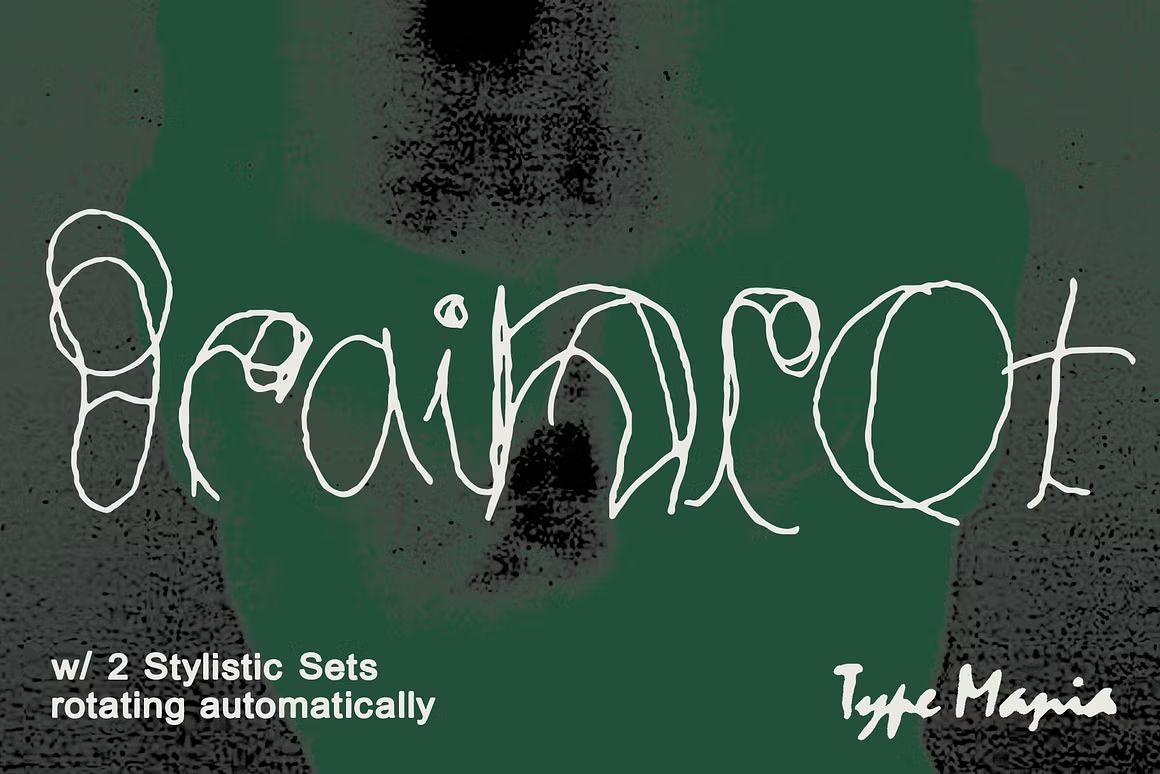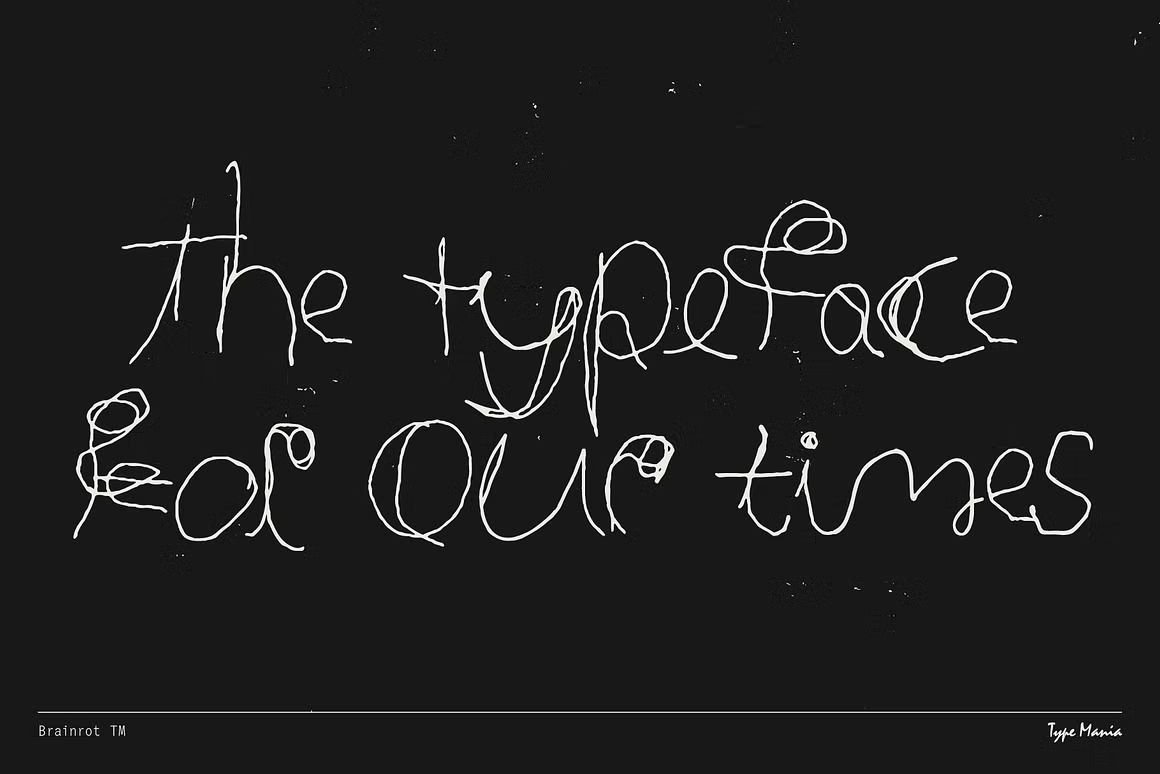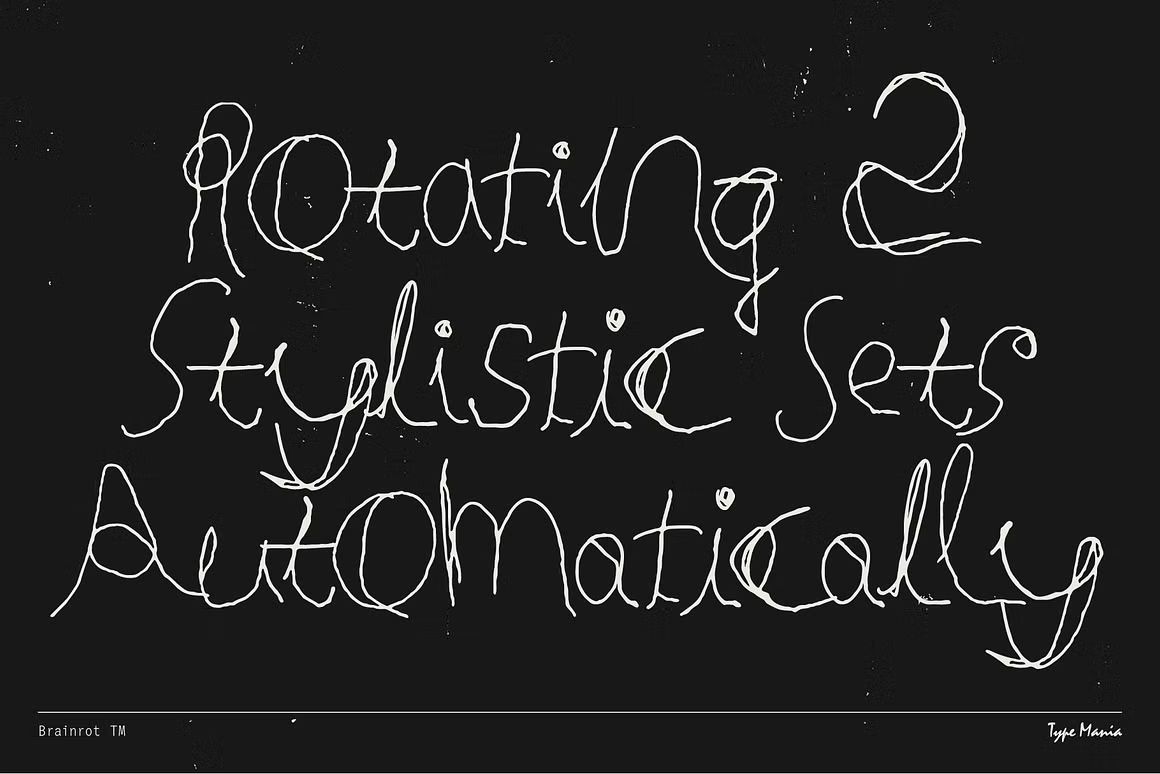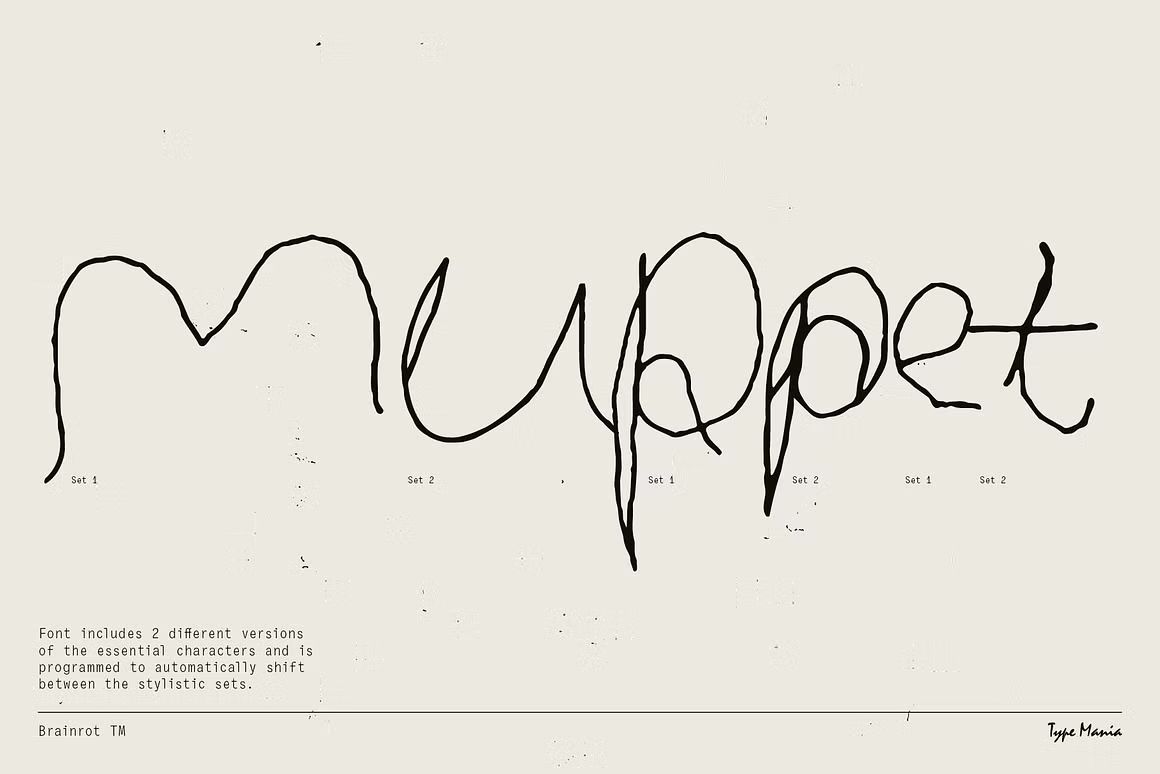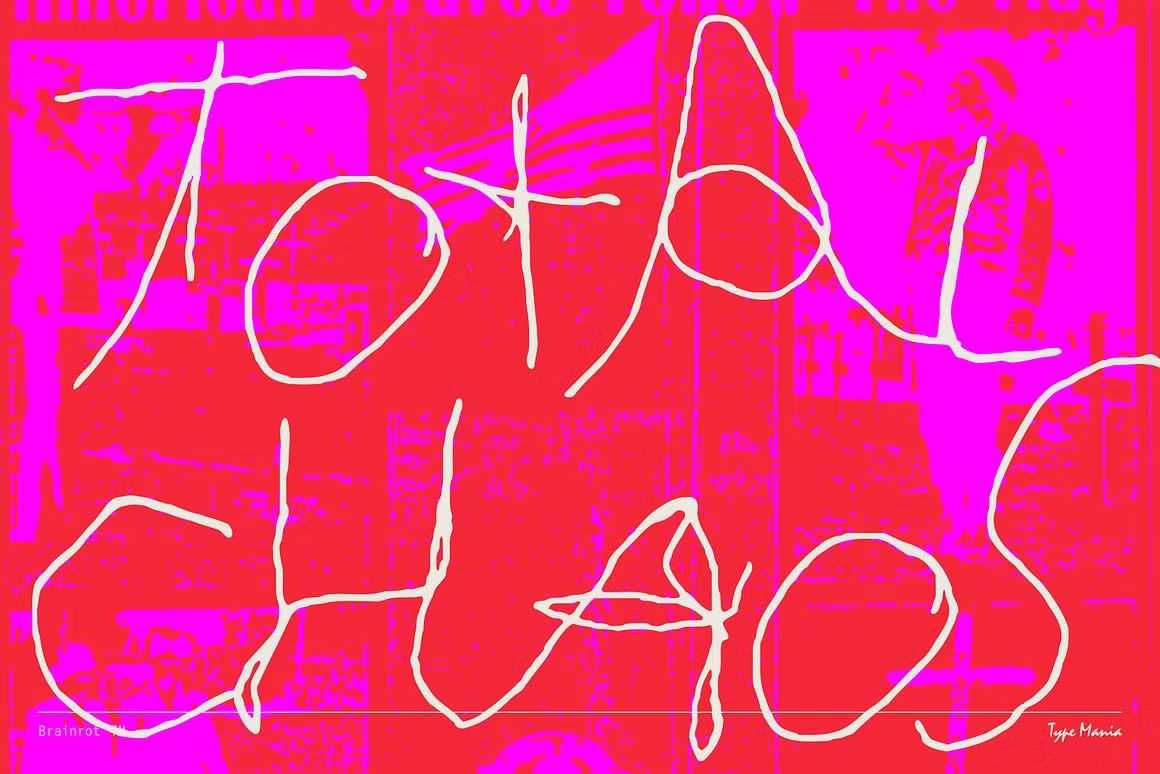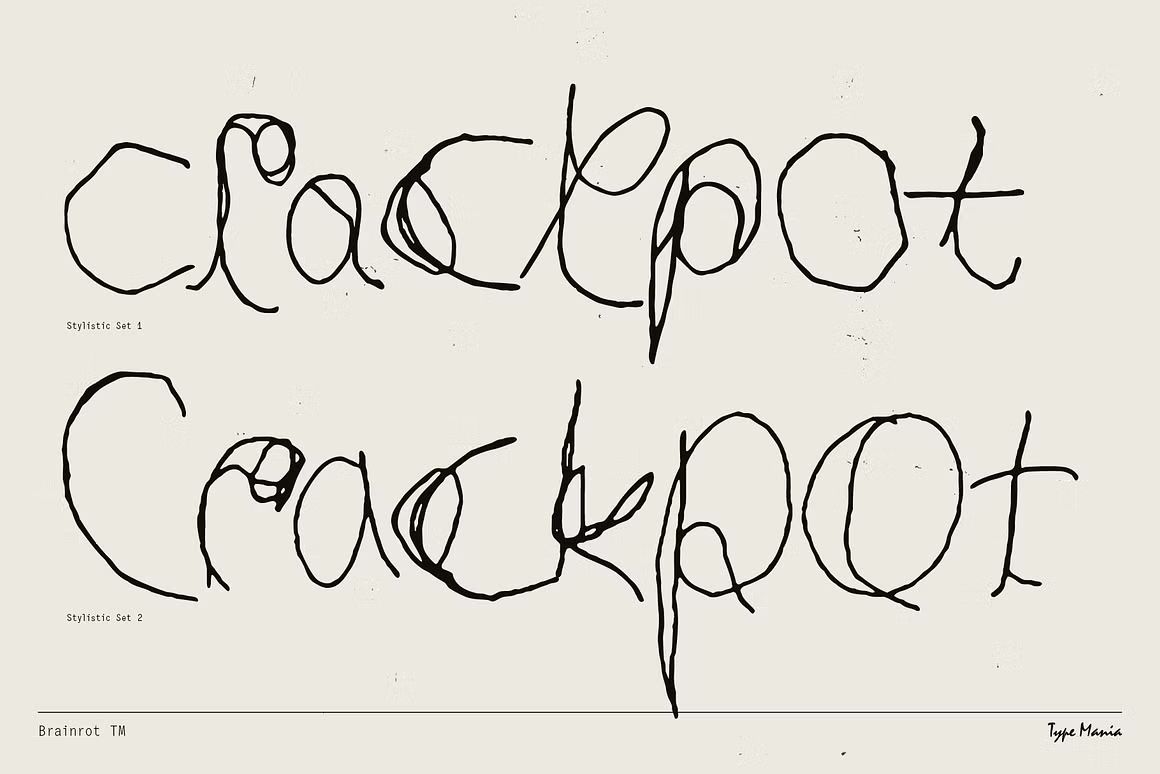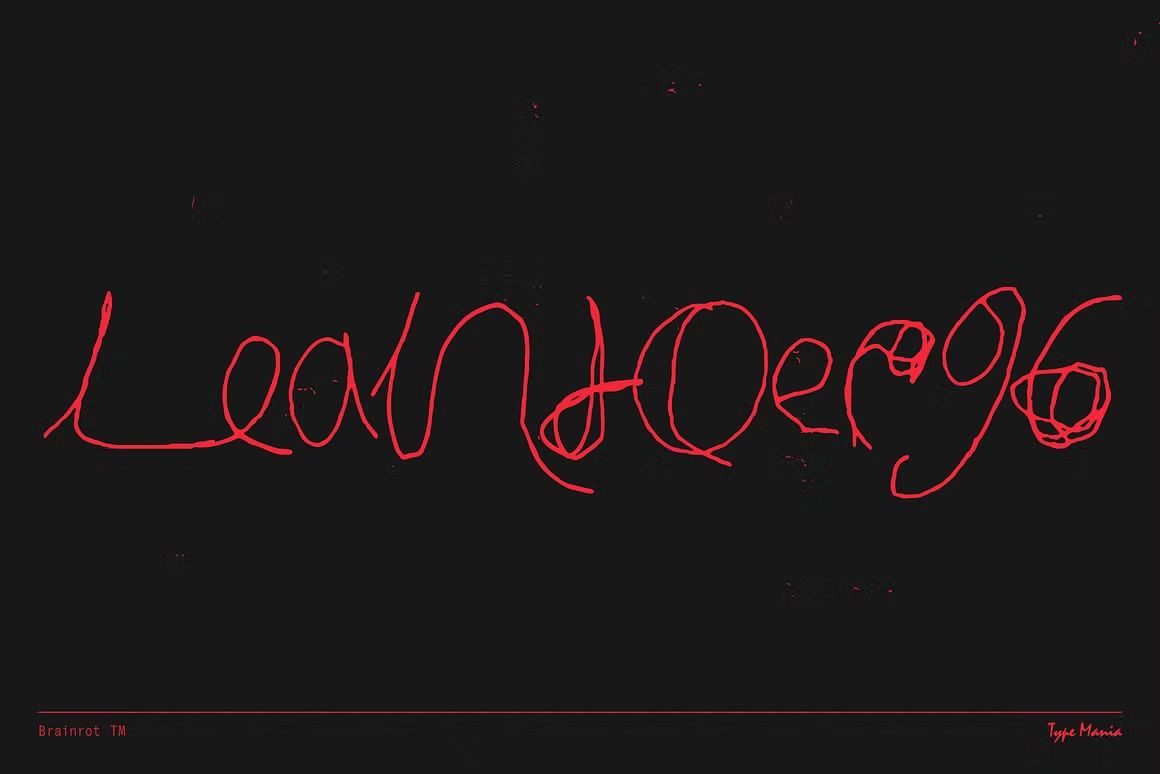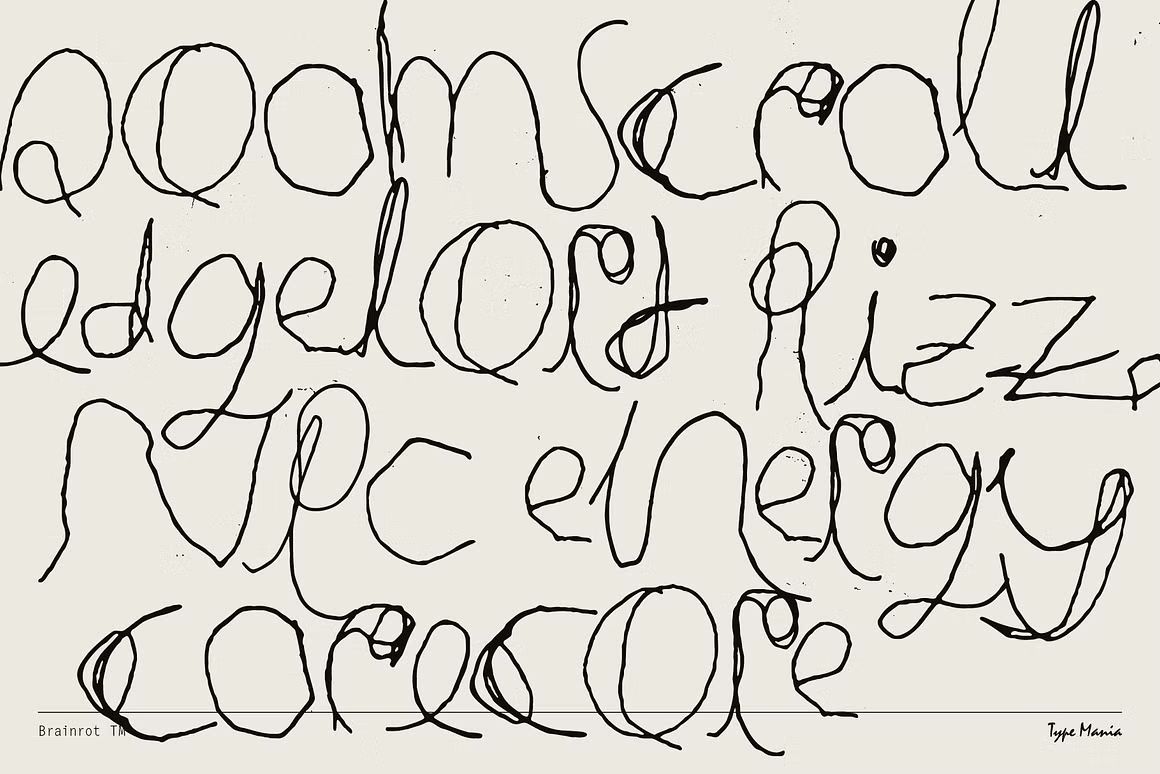
Brainrot TM – Handwritten Font
Brainrot TM adalah font handwritten ekspresif dan liar, cocok untuk desain alternatif dan kreatif. Format OTF/TTF/WOFF, siap digunakan.
Brainrot TM adalah font handwritten bergaya ekspresif dan penuh energi, dengan goresan kasar dan bentuk huruf tak beraturan yang menciptakan kesan bebas, kreatif, dan sedikit “liar”. Sangat cocok untuk desain alternatif seperti poster musik, cover album, zine, ilustrasi indie, atau branding yang ingin tampil unik dan anti-mainstream. Brainrot TM adalah pilihan tepat untuk karya penuh kepribadian dan sikap.
• Handwritten font bergaya bebas, kasar, dan ekspresif
• Ideal untuk desain musik, zine, dan konten kreatif edgy
• Termasuk huruf kapital, kecil, angka, simbol, dan karakter alternatif